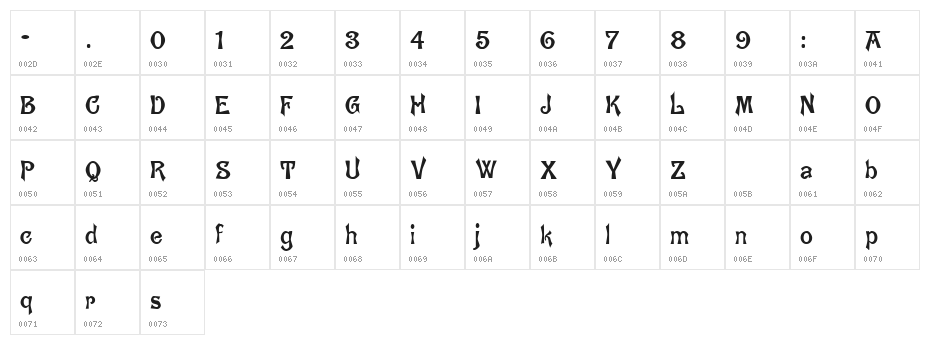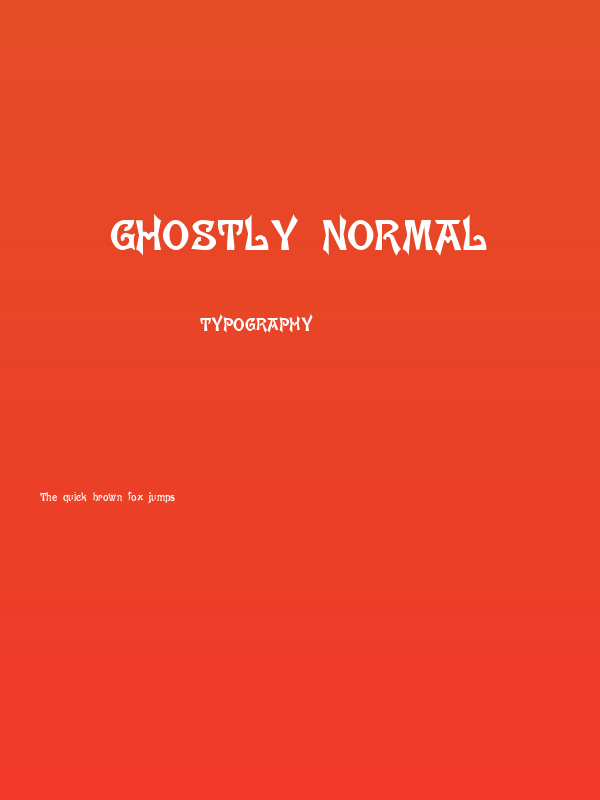
Ghostly Normal Font
| Caz de utilizare | Headlines, Posters, Themed Events |
| Proiecte propuse | Ideal for Halloween-themed designs, horror movie posters, haunted house flyers, and any project requiring a spooky or mysterious vibe. |